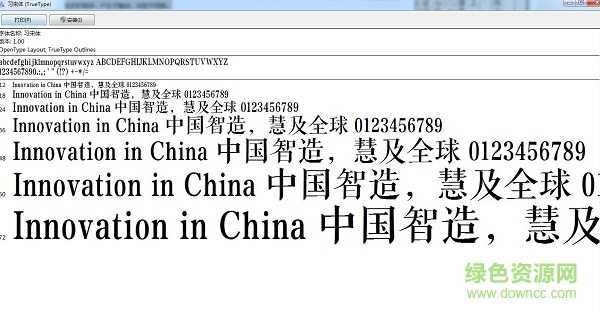
sgsxst習(xí)宋體
sgsxst是什么字體?sgsxst字體又叫習(xí)宋體,是一款美觀新穎的宋體字體,結(jié)構(gòu)簡(jiǎn)潔,排印清晰,適用于網(wǎng)頁(yè)設(shè)計(jì)、書刊報(bào)紙等各個(gè)領(lǐng)域,有需要者快來(lái)本站免費(fèi)下載吧!
sgsxst習(xí)宋體
宋體介紹
宋體是生而具來(lái)的印刷體,產(chǎn)生于雕版,成型于明朝。在宋體字出現(xiàn)之前,印本的字體都是手書的楷體。明初內(nèi)府刻本中的楷書字體還曾傳入朝鮮半島,成為其官方鑄造金屬活字的字體。